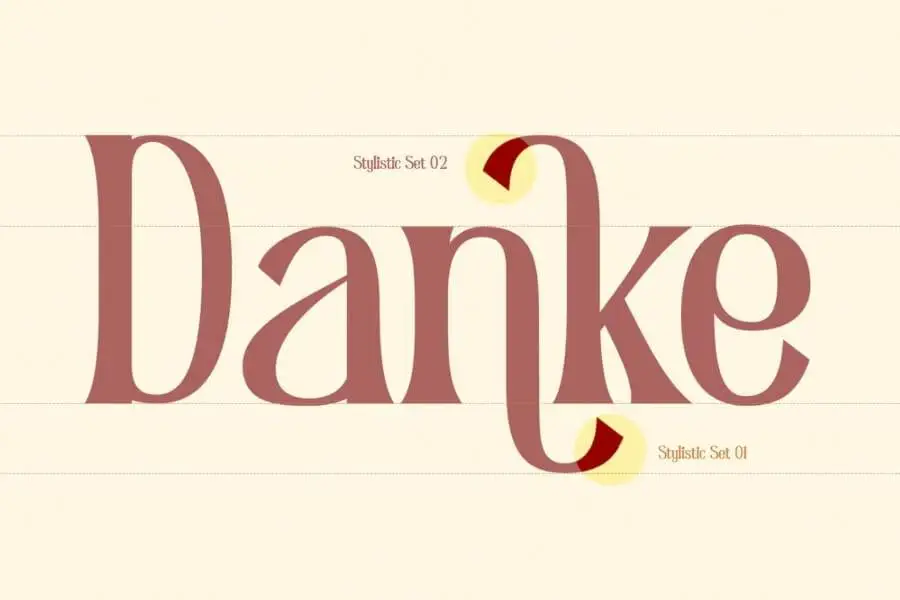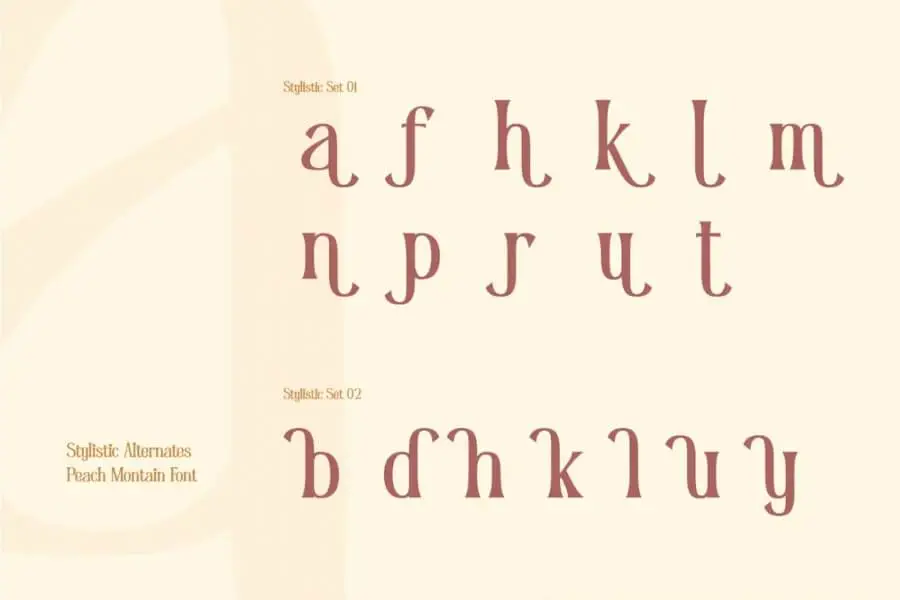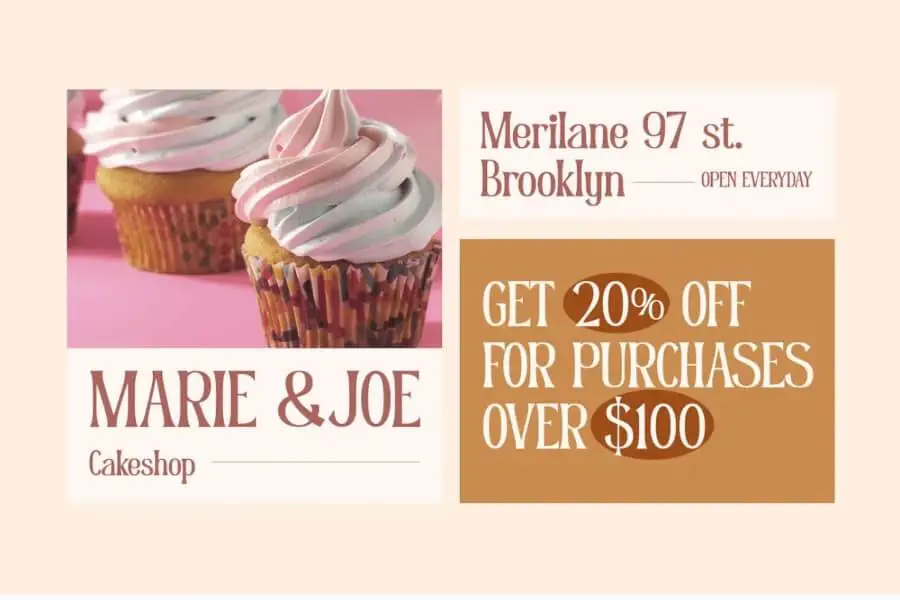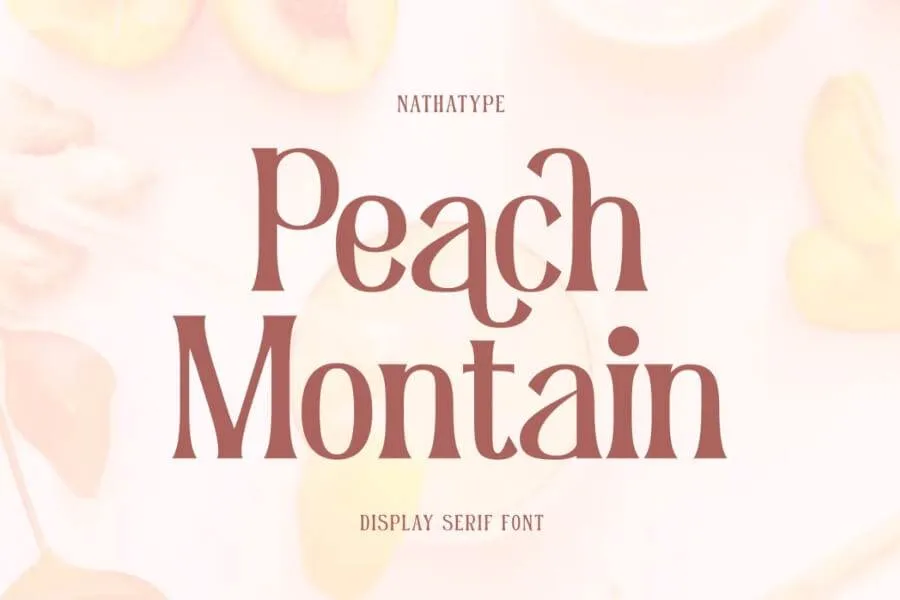
Font Peach Mountain là một phông chữ serif hiển thị thanh lịch, hiện đại, đa năng cần thiết cho các nhà thiết kế ngày nay. Hình thái các chữ cái đơn giản có tỷ lệ tương đối giống nhau. Hơn nữa, độ tương phản cao và khoảng cách rộng của nó thực sự dễ đọc mà bạn có thể áp dụng cho mọi kích thước văn bản.
Ngoài ra, bạn có thể tận dụng những tính năng thú vị có sẵn của phông chữ này để làm đẹp cho thiết kế của mình.
Đặc trưng font:
- Bộ phong cách
- chữ ghép
- Hỗ trợ đa ngôn ngữ
- PUA được mã hóa
- Chữ số và dấu câu
Font Peach Mountain phù hợp nhất cho các dự án thiết kế khác nhau, chẳng hạn như áp phích, biểu ngữ, logo, bìa tạp chí, trích dẫn, tiêu đề, sản phẩm in, thiệp mời, danh thiếp, hàng hóa, mạng xã hội, v.v. Tìm hiểu thêm các cách sử dụng phông chữ này bằng cách tham khảo nhìn vào bản xem trước phông chữ.